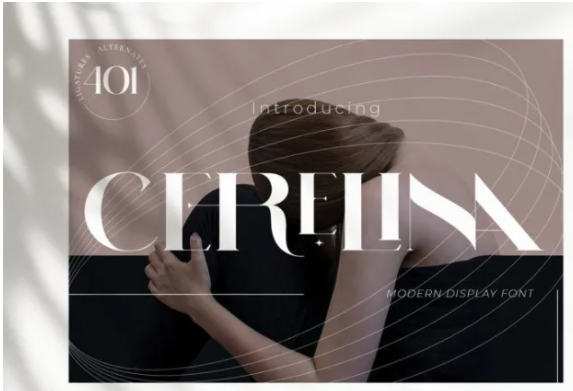
[Fontbundles] Cerelina Font (2021)
Представляем вам Cerelina!
Шрифт для отображения!
Cerelina - современный дисплейный шрифт, состоящий из 401 символа, включая 200+ лигатур.
Cerelina - это идеальный ингредиент для создания заголовка, логотипа, заголовка или любого другого дизайнерского проекта, над которым вы работаете.